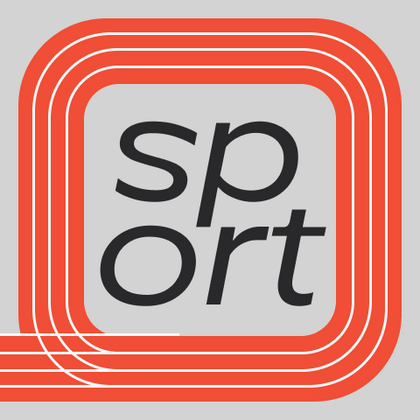
Спортивные шрифты
Ощущение движения, скорости, силы — всё можно подчеркнуть в айдентике брендов с помощью спортивных шрифтов. Это идеальный баланс между брутальностью и четкостью линий. Современные решения от TypeType с продуманной типографикой работают на узнаваемость: от фирменного стиля команд до экипировки и мотивационного мерча. Создайте мощную визуальную идентичность с помощью специальных гарнитур, где каждая буква дышит энергией.
TT Turns — геометрический гротеск с акцентными круглыми знаками и выразительными нависающими элементами. Это универсальный шрифт, который лаконично выглядит и отлично читается в маленьком размере, при этом в крупных кеглях становится акцидентным и проявляет свой характер на максимум. Он энергичный, сильный и динамичный — особенно отчётливо это проявляется в наклонных начертаниях.
TT Supermolot Neue — технологичный модульный гротеск. Это мощный и динамичный шрифт с футуристическим настроением. «Сквадраченные» формы придают ему брутальности, при этом срезанные углы в отдельных элементах делают его пластичным и эргономичным.
TT Neoris — лаконичный неогротеск с безграничными возможностями. Мы уделили особое внимание деталям, cделали наклонные начертания в кириллице визуально отличными от латиницы, соответствующими традиции кириллической каллиграфии.
TT Interphases Pro — неогротеск, который создавался специально для работы в интерфейсах. Среди визуальных особенностей TT Interphases Pro — плавные формы скруглений, повторяющиеся во всех элементах: благодаря им большие массивы текста читаются легко и приятно.
TT Drugs — ленточная антиква: это шрифт без засечек, но с выраженным контрастом.
TT Biersal — акцидентный гротеск со свободным, озорным и авантюрным характером. Отправной точкой для его создания послужил немецкий плакат начала 30-х годов. Мы хотели сохранить не только пропорции, но и ощущение небрежности, живости леттеринга из референса.
TT Paplane — акцидентный сквадраченный гротеск. Так, характерные черты этого гротеска — сквадраченные формы, 45-градусные срезы и обтекаемые внешние контуры.
TT Cometus — современная брусковая антиква. Название гарнитуры отсылает к образу кометы — мощного увесистого тела с красивым хвостом, грациозно рассекающего космические просторы с огромной скоростью.
TT Travels Next — сверхмодный широкий гротеск. Широкие пропорции — одна из отличительных черт этой гарнитуры: знаки почти не сужаются при переходе от толстого начертания к тонкому.
TT Octosquares — октагональный гротеск с футуристическим характером. Этот шрифт отличается геометричностью и своеобразной «мозаичностью»: он как бы собран из отдельных фрагментов, что проявляется и в мельчайших деталях.
TT Globs — стильный брусковый шрифт с широкими пропорциями, живым дружелюбным характером и «летним» настроением.
TT Carvist — современный экспериментальный гротеск со сверхузкими пропорциями. Название гарнитуры отсылает к резьбе по камню: характерные черты этого шрифта — геометричность и брутальность.
TT Ricks — выразительная антиква с острым характером. Создавая ее, мы вдохновлялись шрифтом De Vinne, разработанным Густавом Шредером в 1892 году. Это «злая» антиква, которая, впрочем, иногда усмиряет свой дерзкий нрав.
TT Espina — дисплейная антиква с выразительными засечками. При ее создании дизайнеры вдохновлялись исторической формой буквы «O», которая приобретала ромбовидную форму из-за качества печати. В каждую букву хочется всматриваться, так что заголовки, оформленные TT Espina, точно привлекут внимание.
TT Chocolates — изящный гуманистический гротеск сo сбалансированными пропорциями, близкими к классическим. Шрифт с приятным дружелюбным характером, который интуитивно воспринимается как что-то знакомое.
TT Wellingtons — это гуманистический гротеск, формы которого отсылают к движению ширококонечного пера. Пластичные линии букв обновлённой гарнитуры, присущие английским гуманистическим шрифтам XX века, выглядят актуально и живо в современных дизайнерских проектах.
TT Runs — это выразительный шрифт, который идеально впишется в проекты со спортивной тематикой. При этом гарнитура отлично подойдет и для других современных проектов: после обновления сфера ее применения значительно расширилась.
TT Marxiana является проектом по реконструкции набора дореволюционных шрифтов, которые использовались в изготовлении и печати журнала «Нива» 1887 года выпуска, а именно на его антикве и италике, гротеске и эльзевире.
TT Commons™ Classic является универсальным гротеском с минимальным контрастом штрихов, закрытой апертурой и геометрическими формами знаков. Дизайн гарнитуры разрабатывался для максимально широкого круга задач, с которыми обязан справляться любой качественный корпоративный шрифт.